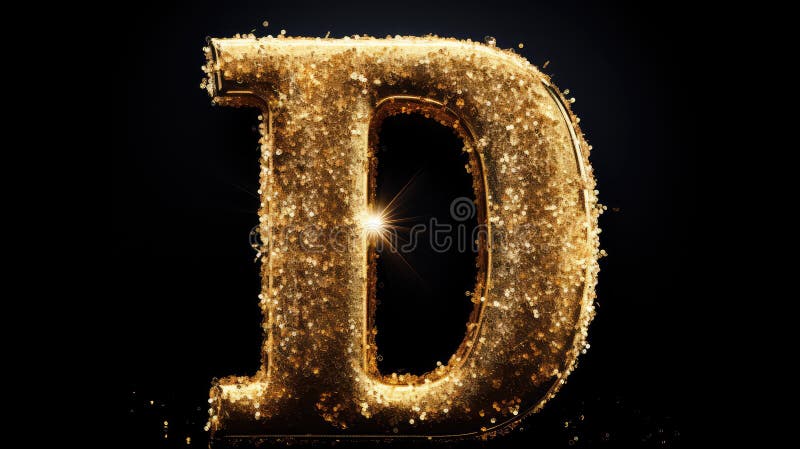
глянцевый золотой шрифт. гламурное золото блеск шрифт иллюстрация блеск типографии дизайн элегантный стильный декоративный гламурный золото блеск шрифт ИИ генерируется